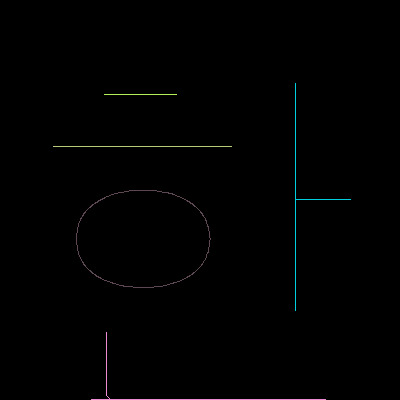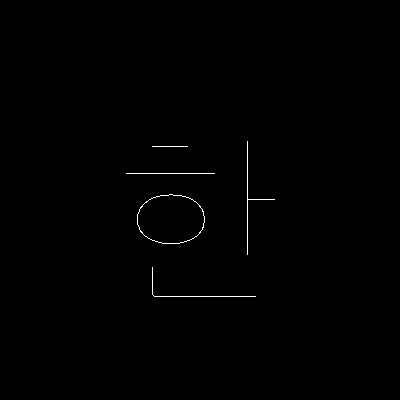
bone 폰트를 잠깐 개발해서 보고 있습니다.
bone 폰트를 잠깐 개발해서 보고 있습니다. 기존 폰트를 읽어서 뼈대에 해당하는 것을 추출하고 다시 획을 3D애니메이션 할 때 쓰는 bone 을 입혀 한글을 뼈로 만들어서 움직이게 하고 있습니다.
한글서체의 기본 글자의 뼈에 해당하는 중심점을 찾습니다. 스트로크로 폰트만드는 작업을 할 때 필요하기도 하고 현재 가장 문제가 되고 있는 글자를 똑바로 쓰지 않는 손글씨의 원점인 기본 획을 찾아내기 위해 만들었습니다.
구분된 글자를 기준으로 다시 OVAL, Line, Square, 등의 기본 도형에 대한 부분을 추출해서 xml 로 대체할 예정입니다. 바로 전에 만든게 초성, 중성, 종성의 위치값을 찾는 것이라면 이번에는 글씨의 기본인 선의 각도 획의 형태를 찾아내는 것입니다.
두깨는 나중일이지만 일단 이 부분만 중점적으로 학습하고 있습니다.
기계학습을 통해서 조금 고민을 하게 되는 것은 비슷한 알고리즘이 되지 않을까 하는 것입니다. 대신 애니메이션이나 새로운 유형의 글자를 만들 때 재미있는 결과물로 확장할 수 있으리라 생각되기는 합니다. 논문 더 봐야할거 같아요 ^^
아무리 엉망으로 써도 bone 추출후 다시 한글폰트로 만들 수 있습니다. 벡터로 만들어 놓은 것을 감안하면 폰트가 조금 달라지지만 손글씨가 아닌 폰트가 됩니다